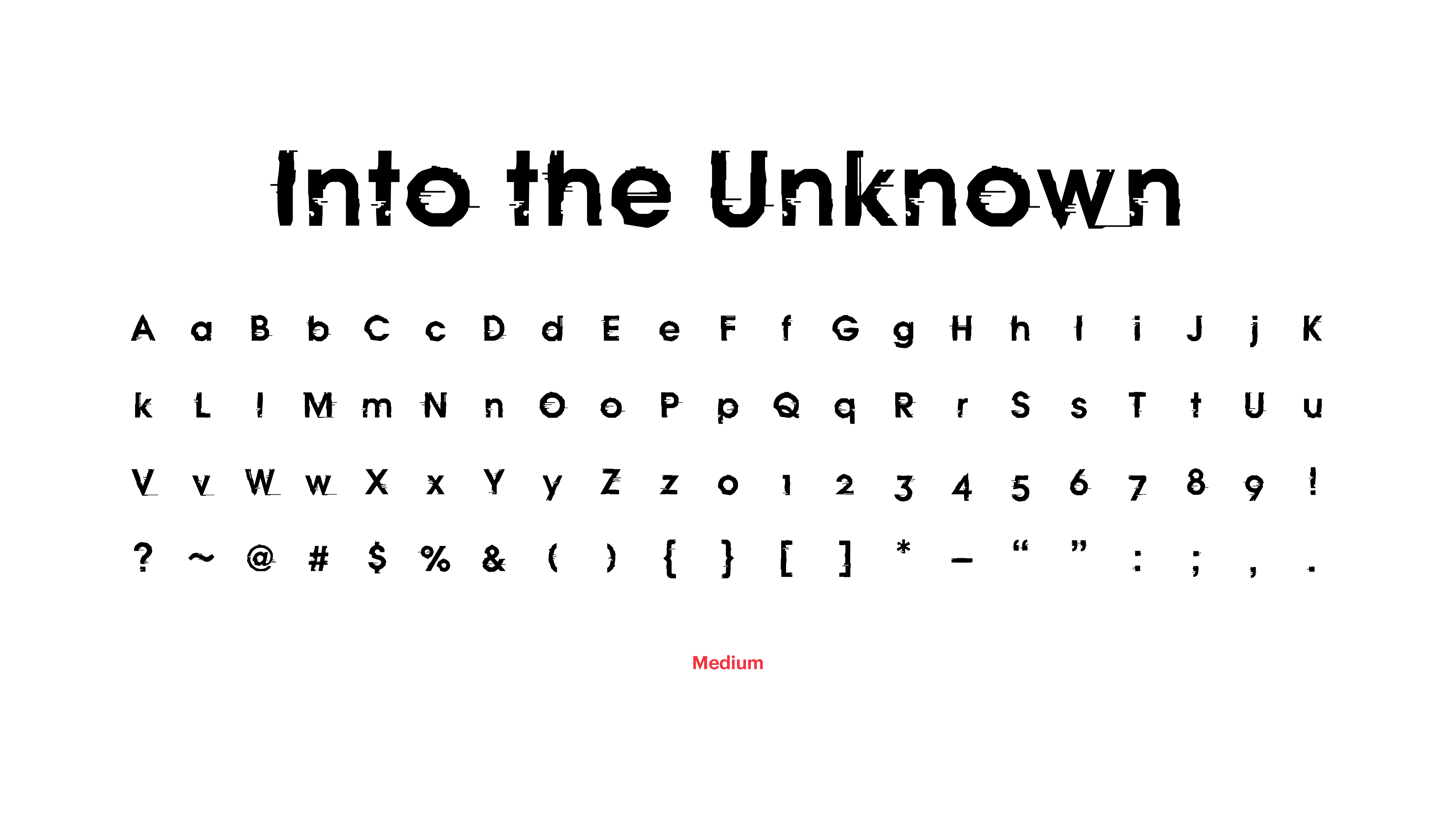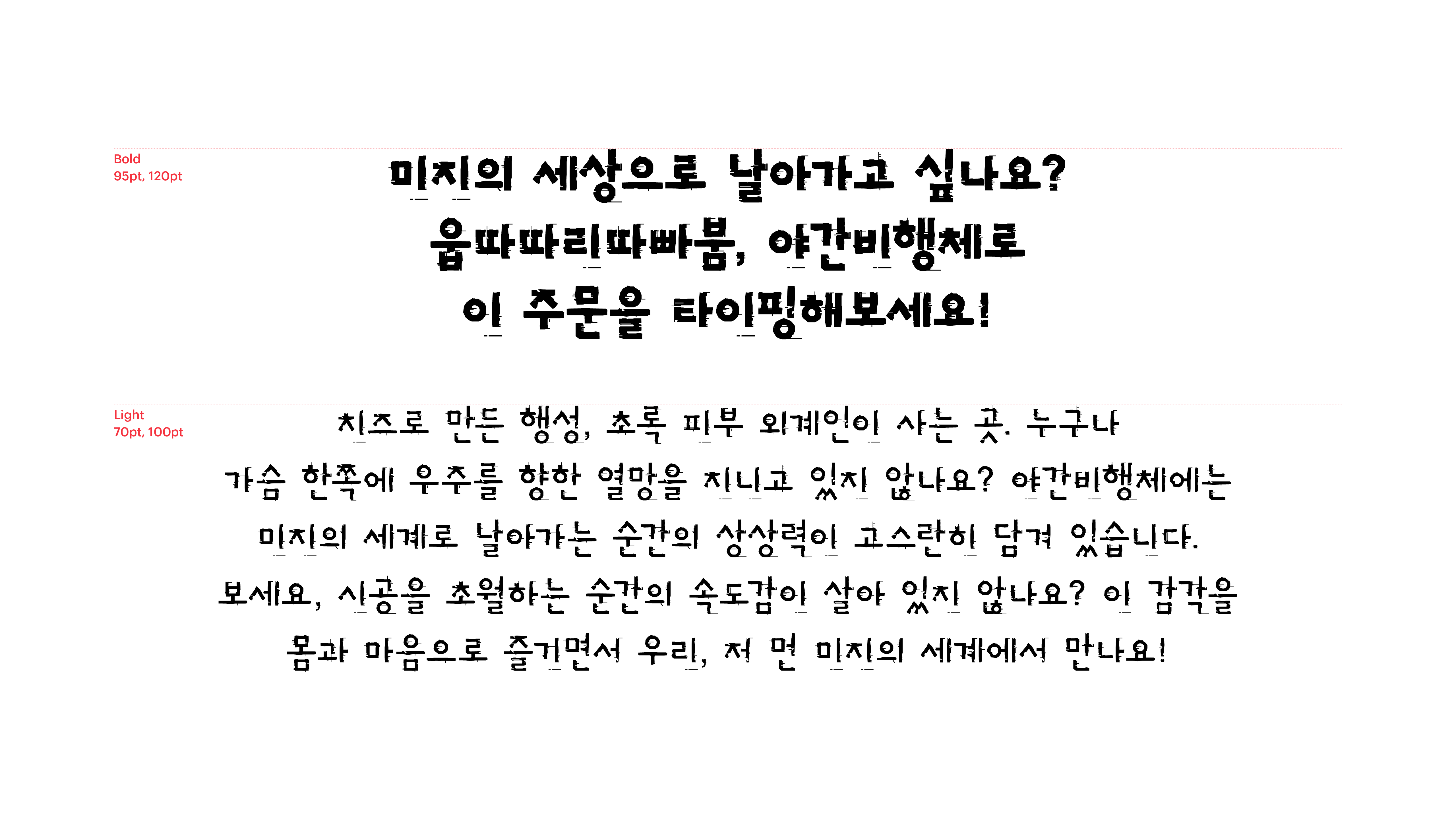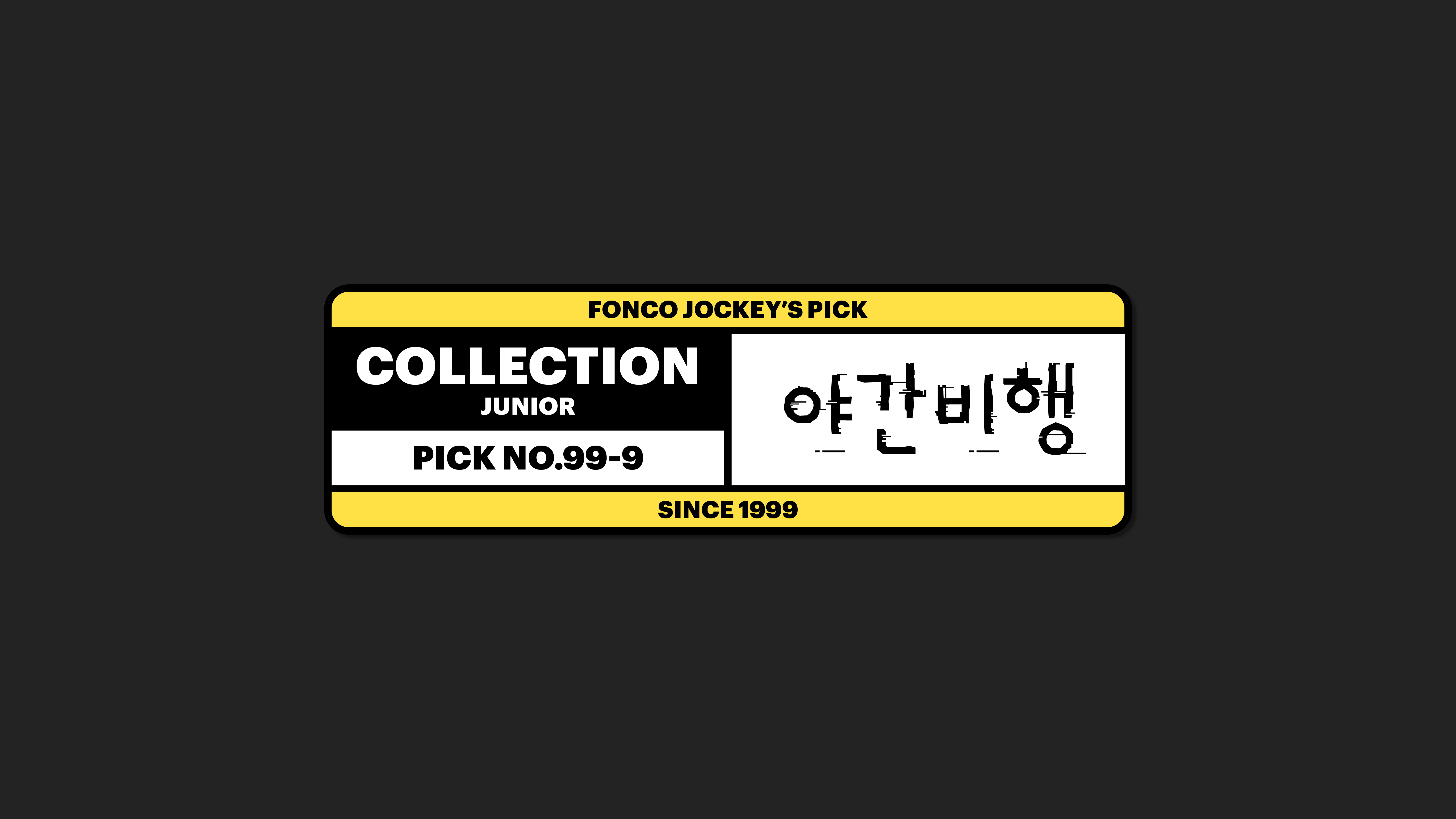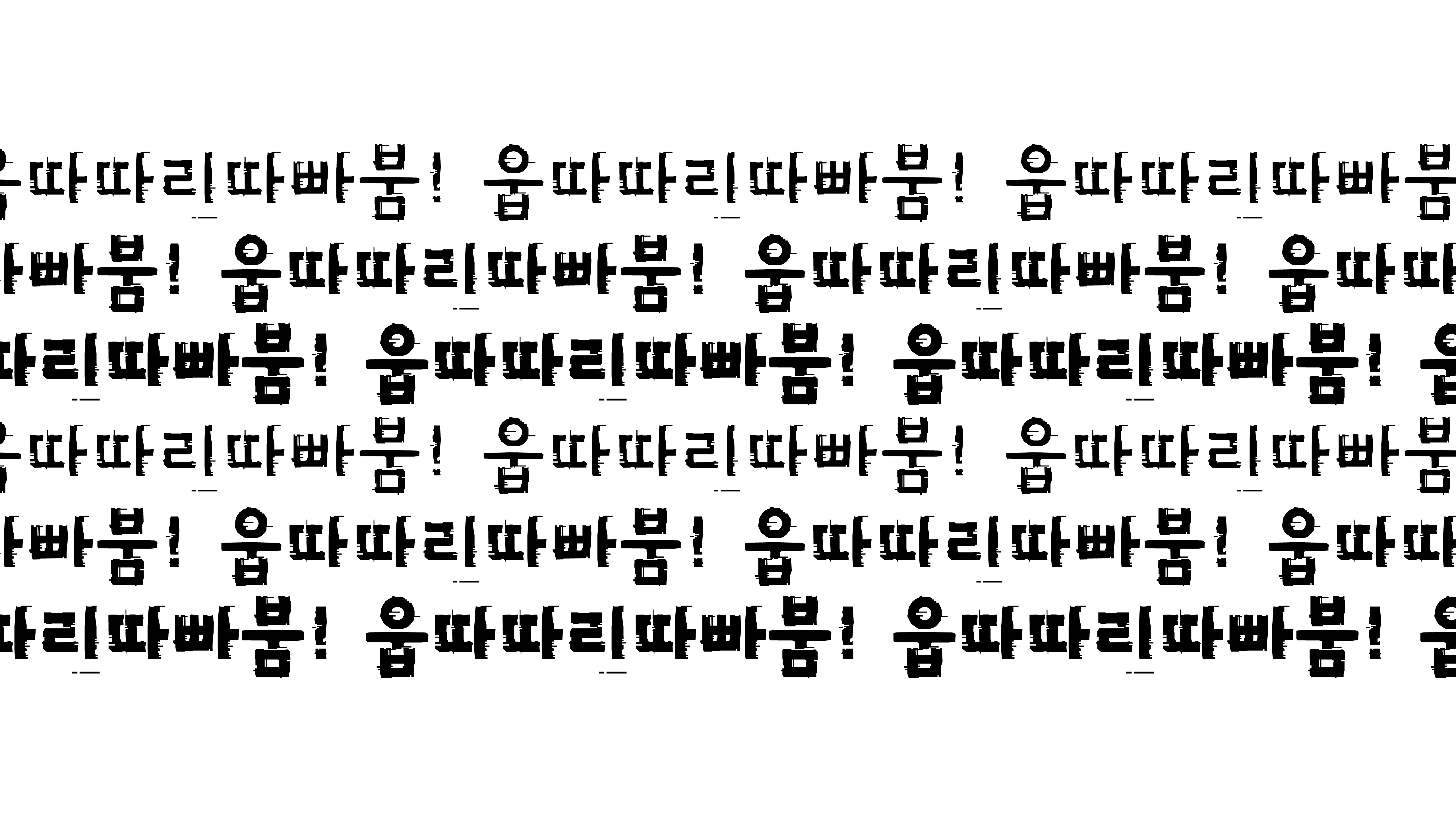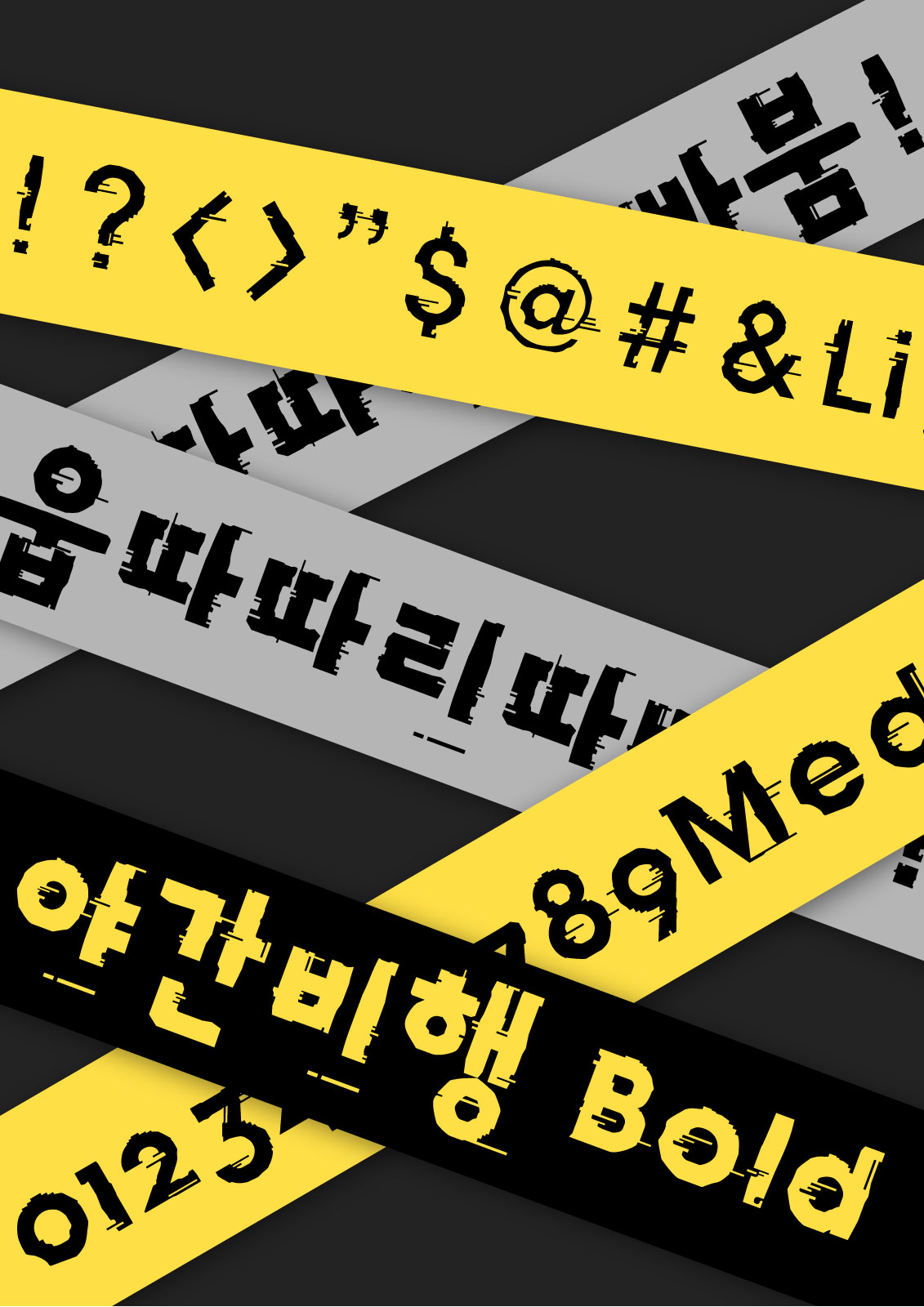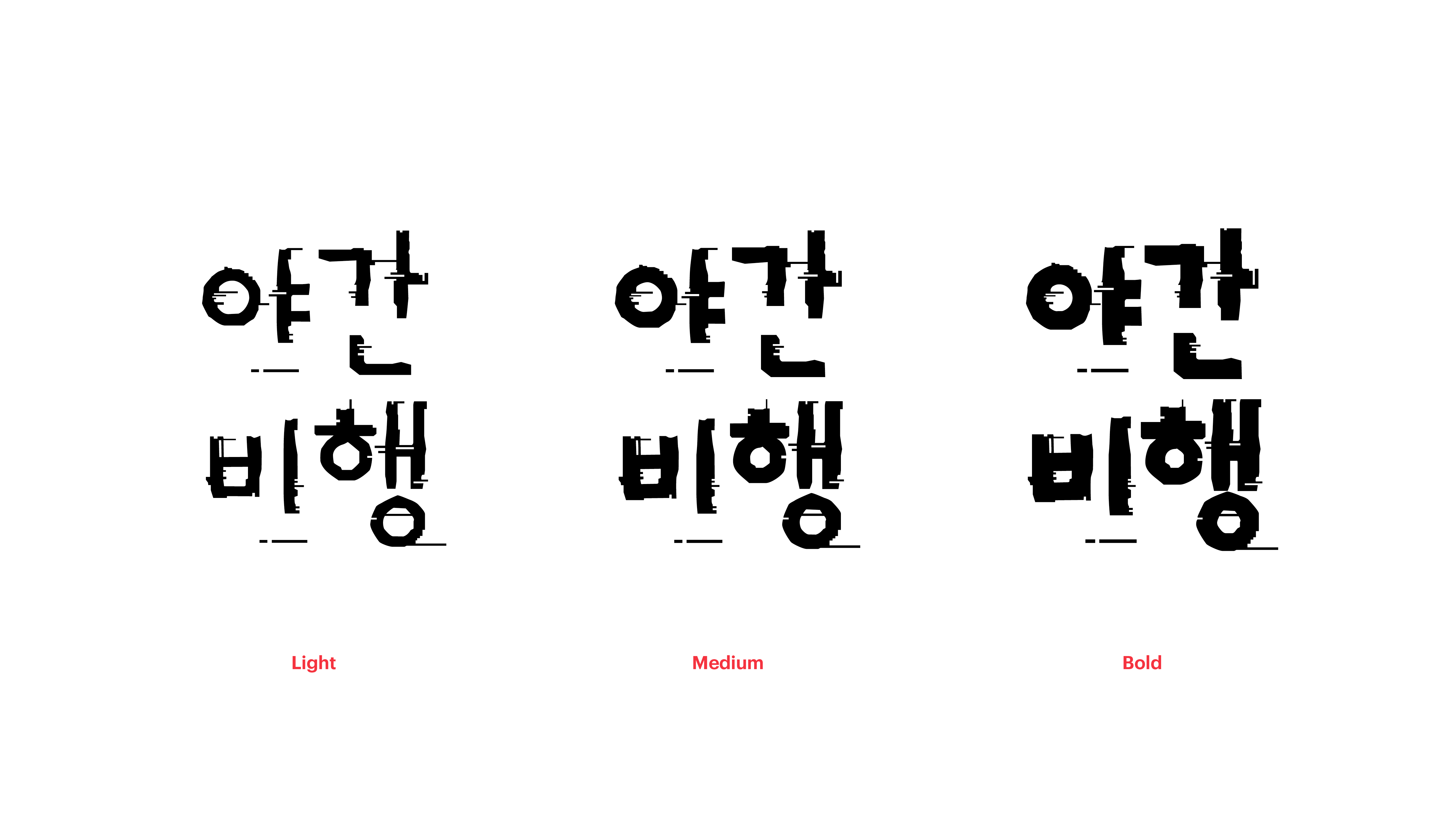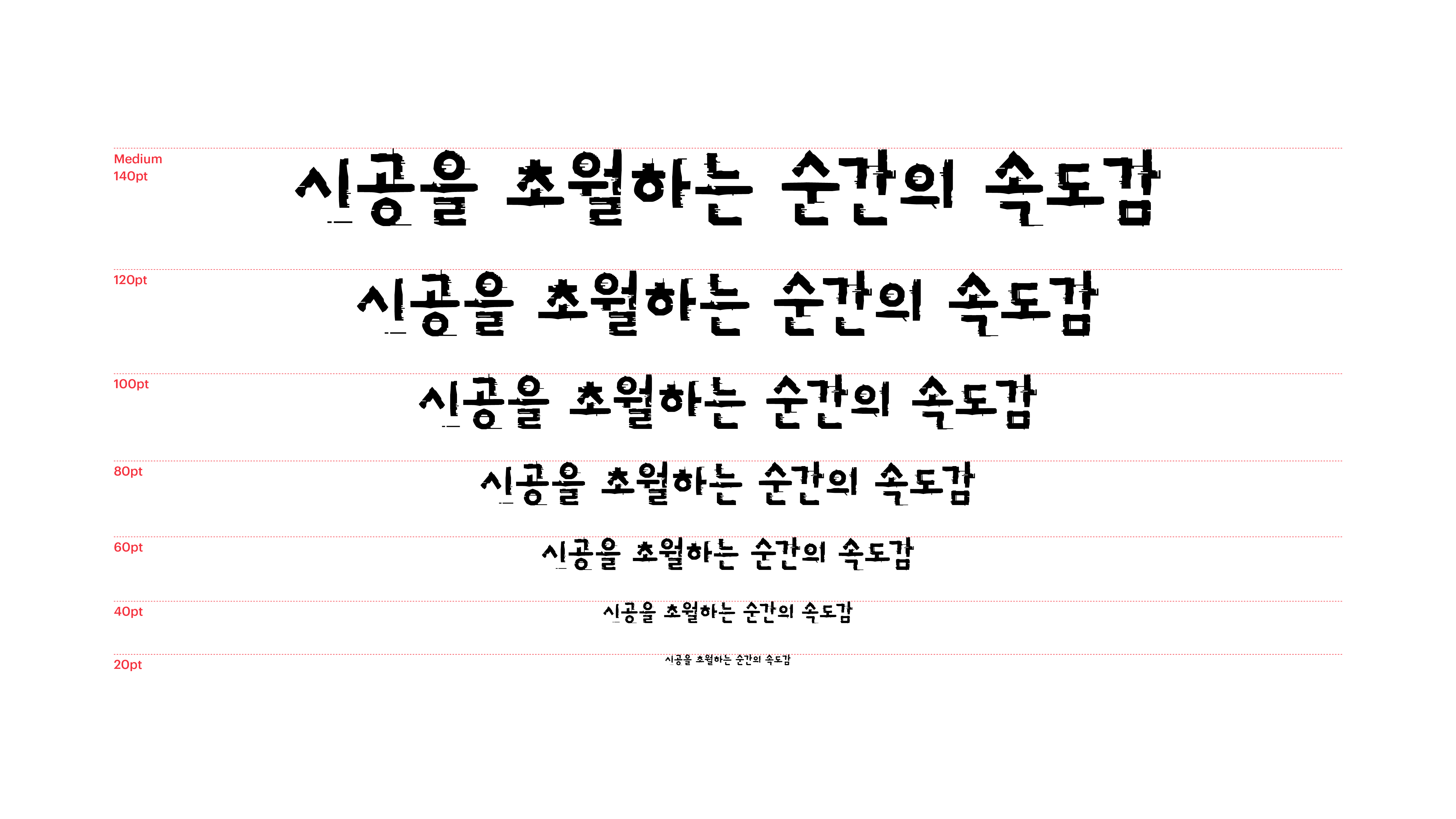
야간비행
Yoon 야간비행
치즈로 만든 행성, 초록 피부 외계인이 사는 곳. 누구나 가슴 한쪽에 우주를 향한 열망을 지니고 있지 않나요? 야간비행체에는 미지의 세계로 날아가는 순간의 상상력이 고스란히 담겨 있습니다. 보세요, 시공을 초월하는 순간의 속도감이 살아 있지 않나요? 이 감각을 몸과 마음으로 즐기면서 우리, 저 먼 미지의 세계에서 만나요!